さて今回は、以前もご紹介したかもしれませんが改めてフォントについてそしてフォントが与える影響についてお話しさせていただきます。
そもそも皆さんフォントを大きく二つに分かれているというのは、ご存知でしょうか?
大きく二つ分ける「ゴシック体」と「明朝体」というもので分かれております。
また欧文フォントというものもありこちらも通常のフォント同様二つに分かれており「サンセリフ」と「セリフ」というもので分かれております。
ではこれら二つのフォントについて詳しくお話させていただきます。
ゴシック体
縦横の太さが均等それこそがゴシック体の特徴といわれております。また、ゴシック体はその性質上、男性的な印象を与えているとも言われております。
ゴシック体の特徴としてはサイズを小さくしても目立つこともありチラシや時刻表などに使用されております。
ではここで画像で明朝体とくらべてみました。
上部画像で挙げられることは、
・赤丸のようなセリフがついていない。
・青丸のように文字にはねやはらいが一切ない。
ことが上げられています。
またゴシック体は全体的に動きが少なく、統一感がある雰囲気ということがわかります。
明朝体
繊細さや優雅な印象を与えるフォントそれこそが明朝体。筆使いを感じるフォントなので、和のテイストや伝統を感じるものと相性が良いです。
また細いフォントであれば高級感や誠実さを与えることができ、太いフォントであれば大人ぽさや固い印象を与えることもできます。
ゴシック体との違いとしては
・文字が太くなると元気で力強くなる分、明朝体本来の特徴が薄くなる
・強弱や動きのあるため大人っぽい印象を受けやすい
などがあります。
筆で書いた字の特徴をそのまま受け継いだということが分かると思いますが、線の太さも強弱があり動きがある印象を受けることがわかります。
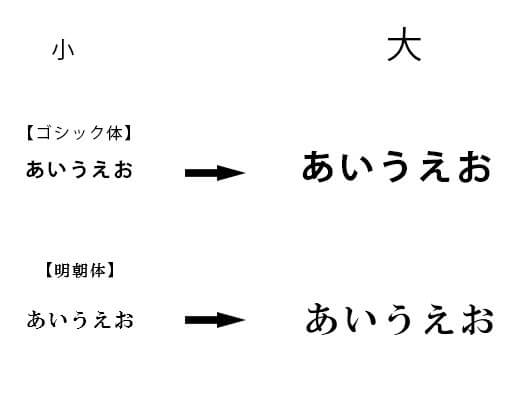
また上部画像のように文字の大きさの違いによって、見た目の印象もがらっと変わります。大きくなるほど、元気で親近感を感じさせやすくなります。逆に落ち着いた感じにしたい場合は小さめの文字にすると良いと思います。
まとめ
いかがでしたでしょうか?ゴシック体、明朝体の良さが改めてわかりそして使用する場面がはっきりとわかりました。これからデザインをする上で更にフォントについて注意深くなりデザインをしていこうと思います。次回はフォントのテクニックについてお話させていただきます、それでは。